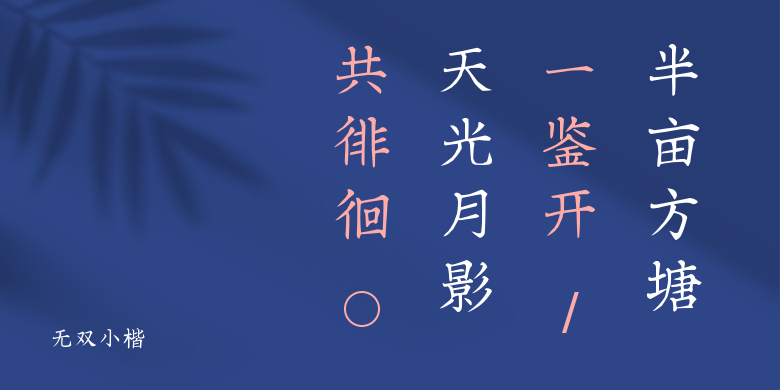
无双小楷
无双小楷,这款字体结构工整、笔画清晰,兼顾美观与易读性,适用于标题、正文、海报、包装、LOGO 等多种场景。字形优雅稳定,风格百搭耐看,适配日常排版与创意设计,让文字呈现更舒适、更具质感。无双小楷一笔一画,皆是细节,以均衡的比例、流畅的线条打造舒适视觉体验,字形端正大气,风格简约现代。无论是商业设计、品牌宣传还是日常排版,都能轻松驾驭,让文字更有格调与力量。无双小楷字体下载。